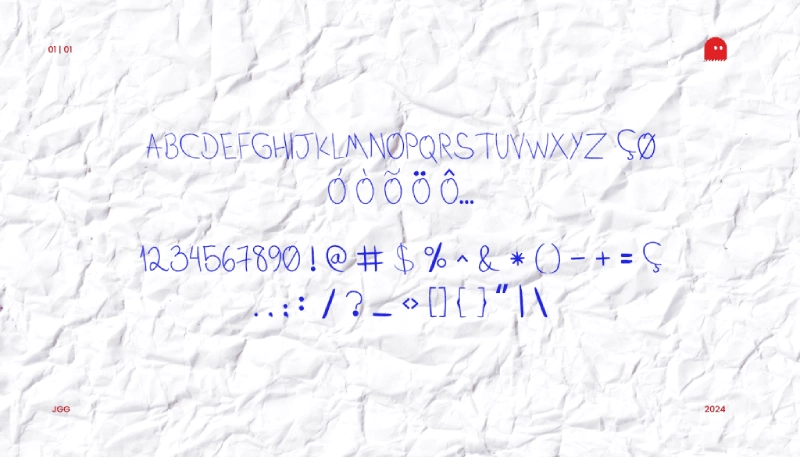
فونت انگلیسی دست نویس Historic
Handwritten Fonts: Historic
فونت Historic یک تایپ‌فیس مدرن و دست‌نویس است که سرشار از خلاقیت و جذابیت می‌باشد. خطوط بازیگوش و طراحی کمی نامنظم آن، جلوه‌ای طبیعی و دست‌ساز به متن می‌بخشد و حس صمیمیت و دسترسی‌پذیری ایجاد می‌کند.
ویژگی‌های کلیدی فونت Historic
یکی از برجسته‌ترین ویژگی‌های این فونت، اصالت و گرمای آن است. هر حرف به‌گونه‌ای طراحی شده که انگار با دقت و ظرافت توسط دست کشیده شده است و همین موضوع به طرح‌های شما حالتی منحصر‌به‌فرد و شخصی می‌دهد. این ویژگی، Historic را به انتخابی ایده‌آل برای پروژه‌های هنری و مواد برندینگ تبدیل می‌کند که هدفشان ایجاد ارتباطی معنادار با مخاطب است.
کاربردهای متنوع در طراحی
فونت Historic در زمینه‌های مختلف طراحی می‌درخشد، از دعوت‌نامه‌ها و پوسترها گرفته تا گرافیک‌های شبکه‌های اجتماعی. ظاهر پررنگ اما درعین‌حال راحت و غیررسمی آن، گزینه‌ای عالی برای کارت‌های تبریک، برندینگ بوتیک‌ها و هر پروژه‌ای است که به اصالت و سرزندگی نیاز دارد.